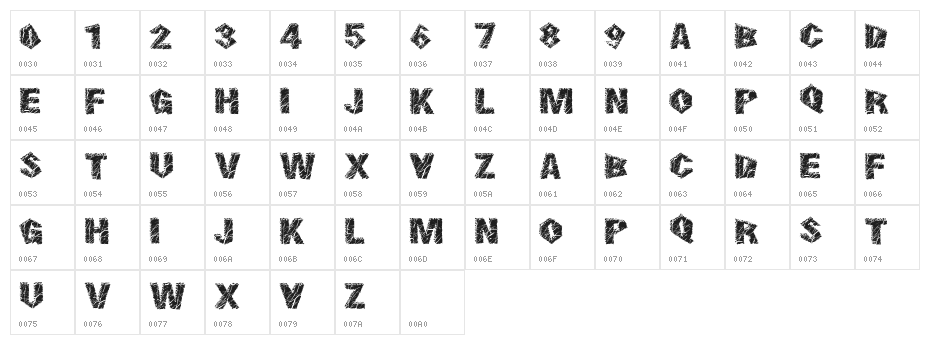
SmokingCracks Font
✎ Distorted Eroded
| Categorie | Distorted Eroded |
| Stile generale | Urban, Edgy, Artistic |
| Progetti proposti | Ideal for album covers, streetwear branding, posters, and urban-themed designs. |